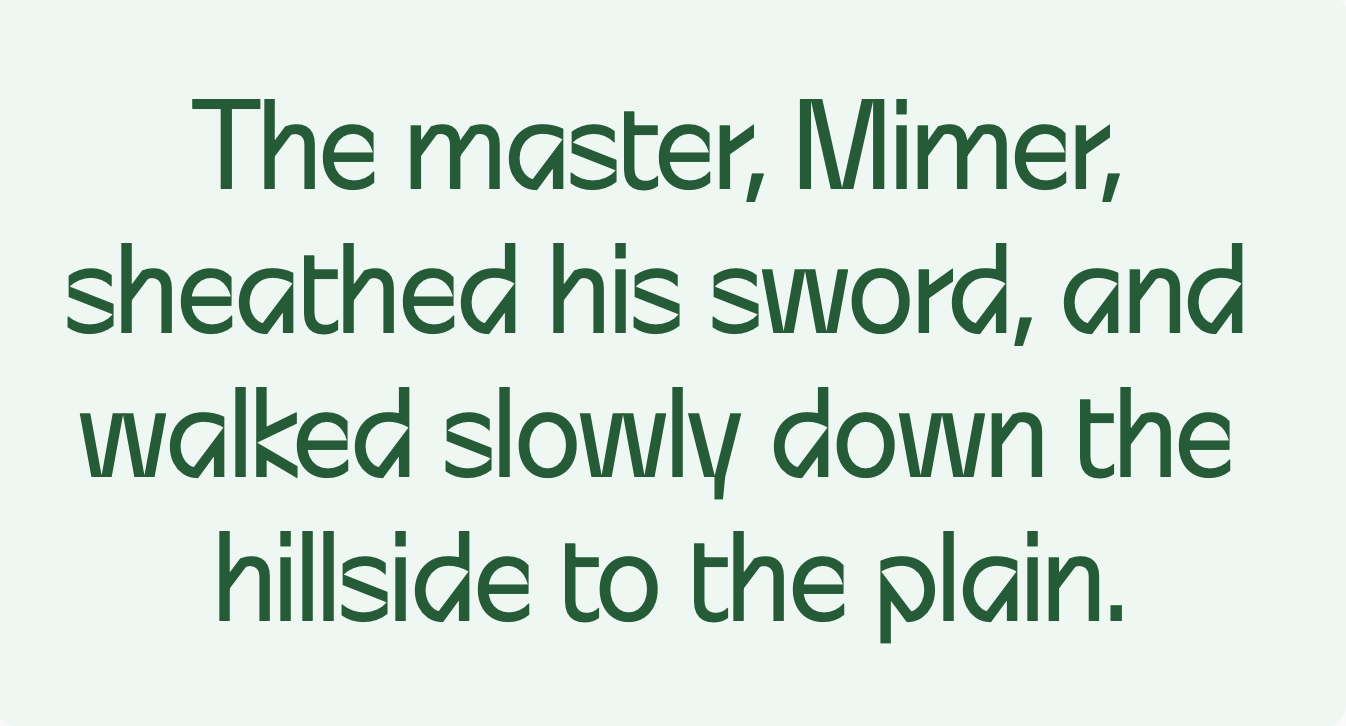
Serifenlose mit abgesägten Lettern (z.B. A, M, N, V, W ...) aka Sägewerk Grotesk
Dachte zunächst, die taugt auch als Circular-Alternative aber bei genauerem Hinsehen erscheinen einige Kurven ziemlich unelegant (siehe beispielsweise S, a und e). 🤷🏼‍♂️